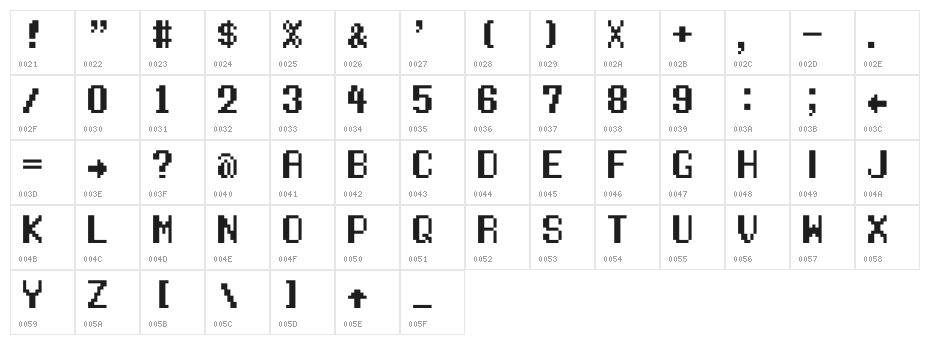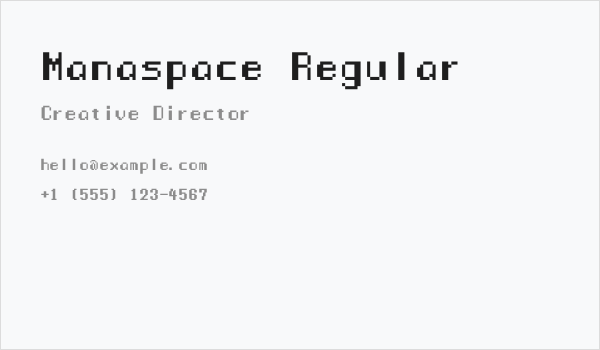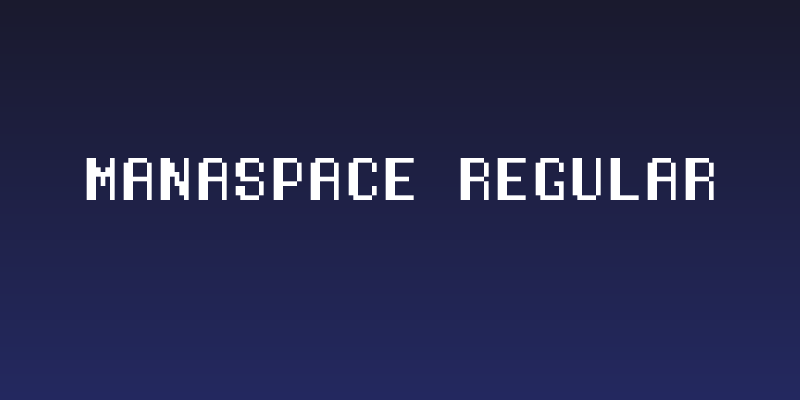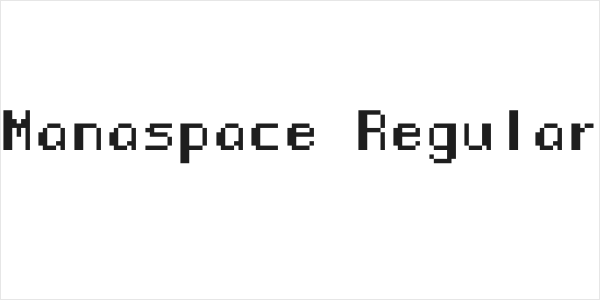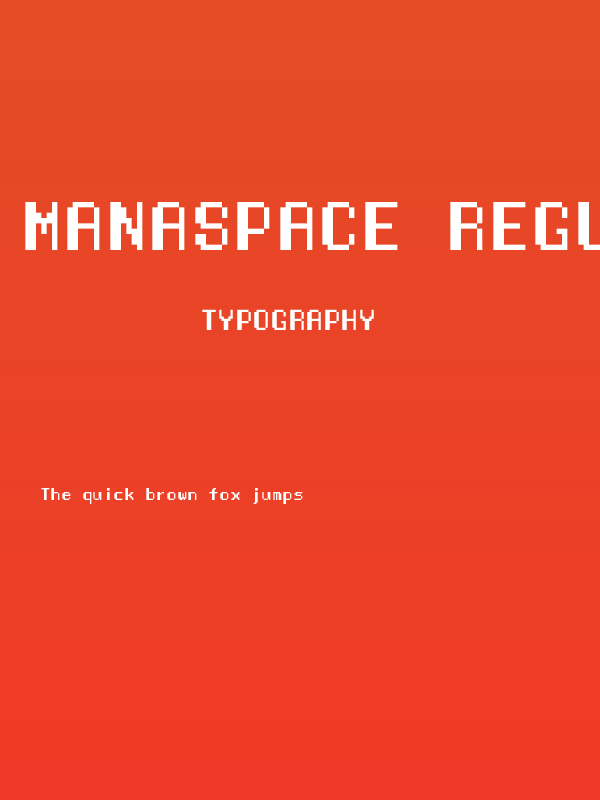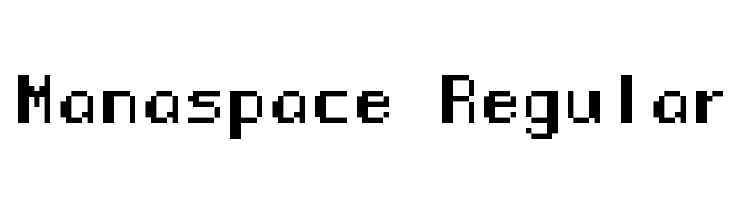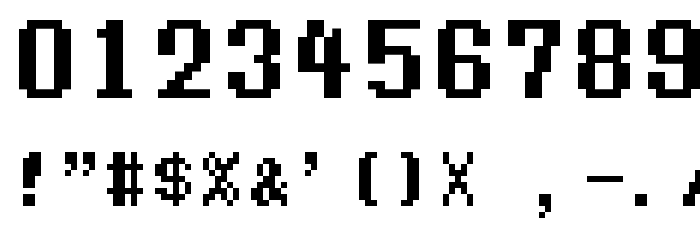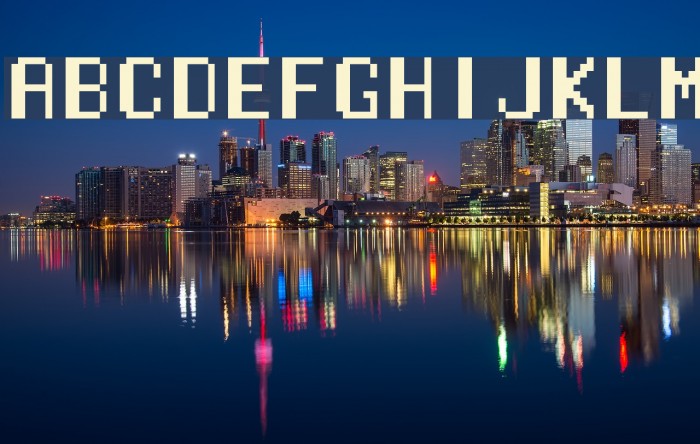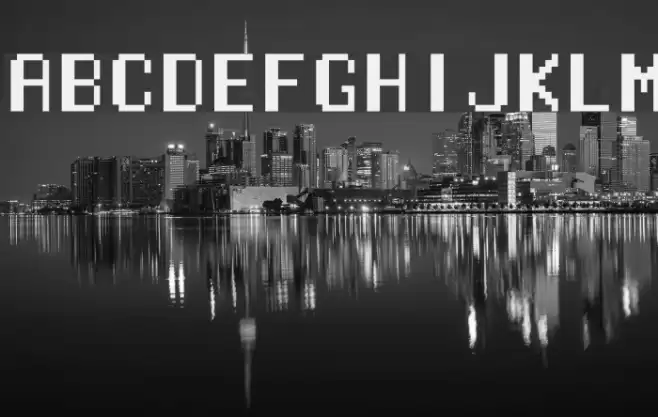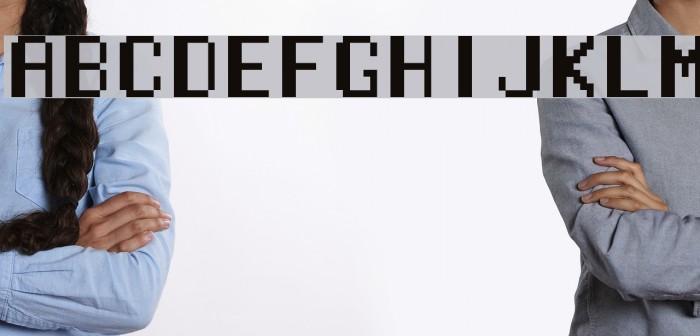
Manaspace Regular Font
✎ Pixel
| Общий стиль | Retro, Digital |
| Область применения | Coding, Digital art, Retro-themed designs |
| Рекомендуемые проекты | Ideal for retro video games, coding environments, digital art projects, and any design requiring a nostalgic or tech-inspired look. |